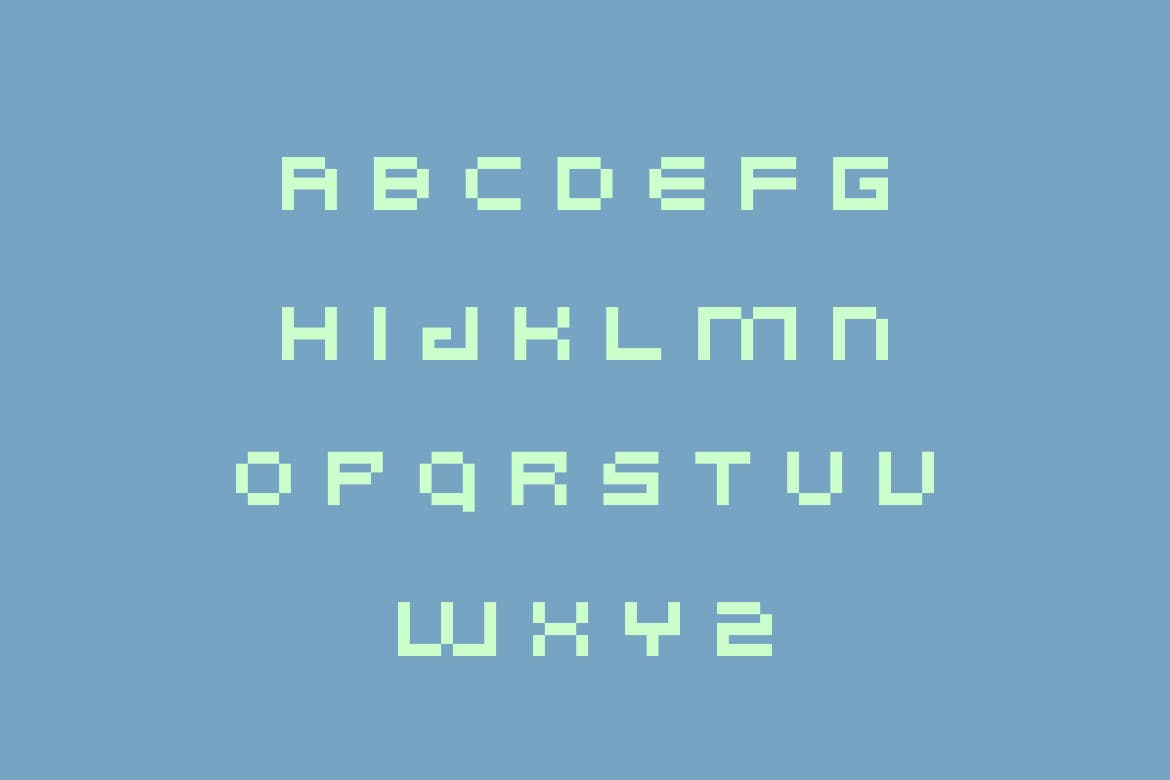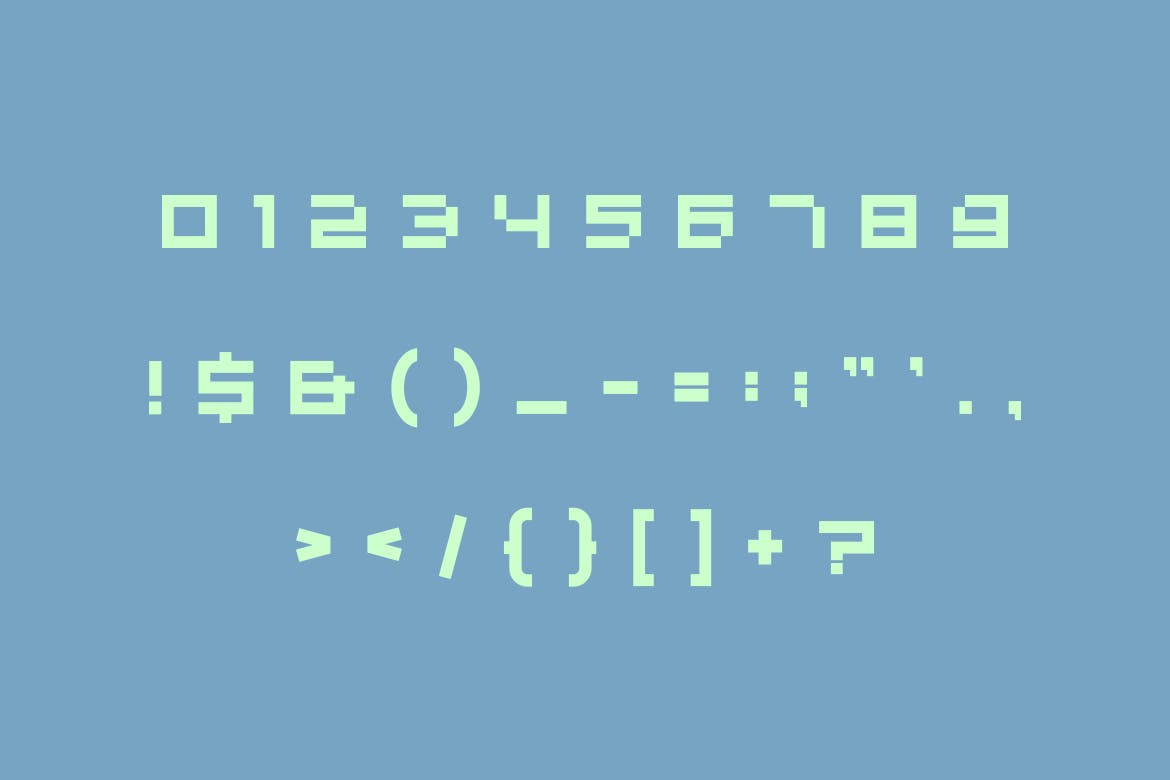
محصول جدید ما، فونت Craft Fone - فونت مدرن را معرفی میکنیم.
فونت Craft Fone - فونت مدرن یک فونت نمایشی جسور و اصیل است. این فونت برای هر پروژه برندینگ، مانند طراحی لوگو، چاپ تیشرت، ورزشهای الکترونیکی و موارد بسیار دیگر مناسب است و در طیف وسیعی از زمینهها به خوبی عمل میکند.